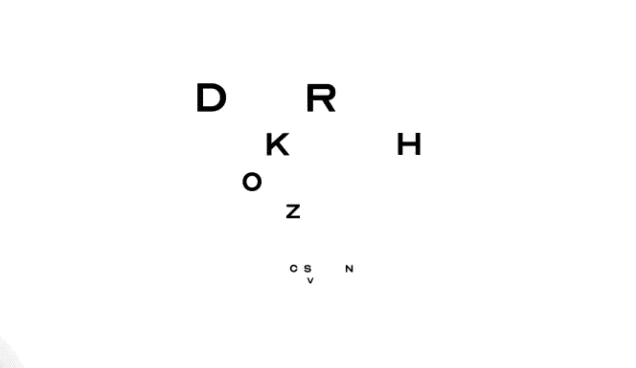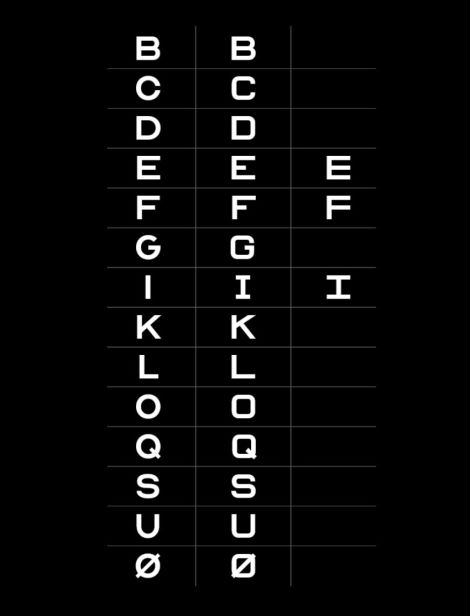
フォントにこだわる人には、たまらないデザイン。
現在、無料でダウンロード可能になっている「Optician Sans」フォントは、もともとノルウェーの眼科Optician-Kのリブランディングプロジェクトとして、デザイン会社ANTI Hamarによって誕生しました。Fast Companyがこのフォントの成り立ちについて明らかにしています。
インタビューによるとOptician Sansフォントのモチーフとなっているのは、1862年にオランダ人眼科医のHermann Snellenさんが患者の視力を測るのに開発した文字デザイン。ANTI HAmarは新たなフォントを作るにあたって、スネレン試視力表で使用されていた10 文字(CDHKNORSVZ)をベースに、5x5 グリッドを適用しました。
1959年、これに変更を加えたのがアメリカの眼科医 Louise Sloanさん。上記GIFの「E」など、特徴的なひげ飾りの部分が見直されました。のちにまた新たなレイアウトに変更され、現在世界中の眼科などで使用されているLogMAR視力検査が誕生しました。
ANTI HamarはOptician Sansフォントを作るにあたりSloanさんのデザインを参考にしましたが、AからZまでのアルファベットが揃っているわけではないため、たった10文字(そのうち母音にいたっては「O」の1文字のみ)をもとにアルファベットの文字と数字デザインを創り出す必要がありました。
ANTI Hamarでアートディレクターを務めるSimen SchikulskiさんはFast Companyに、次のように答えています。
いくつか変更が必要な部分もありましたが、それ以外の部分はかなり保守的にしました。
フォントでなく眼科検診のためにつくられたものであったため、もとの文字のままでは我々の想像していたところとはちがう形やサイズになっていました。
視力検査のために作られた文字では、たとえば「C」と 「O」を見分けるのを難しくしてあるなどの特徴があったため、デザインの変更が必要だったのです。
タイプデザイナー でリスボンにある大学IADEでタイポグラフィーの教鞭をとるFábio Duarte Martinsさんも、同プロジェクトに参加。米Gizmodoの取材に対して、メールで以下のように回答してくれました。
視力表は視力を測定するためにつくられたものですから、たとえばストローク幅が均等であることが重要になります。我々はOptician Sansフォントを使って何か測定したいわけではなく、ビジュアル的に魅力的なフォントをつくることを目的としていました。
最後に、Martinsさんらは自分たちが楽しんだのと同じように人々がこのフォントを楽しんでくれることを願うと言っていました。現在、より多くの言語に対応できるよう取り組んでいるとのことです。
日本の視力検査ではアルファベットの「C」タイプが一般的ですよね。もし日本語版のOptician Sansフォントができたら、平仮名やカタカナはまだしも、漢字はどんな書体になるんでしょう。